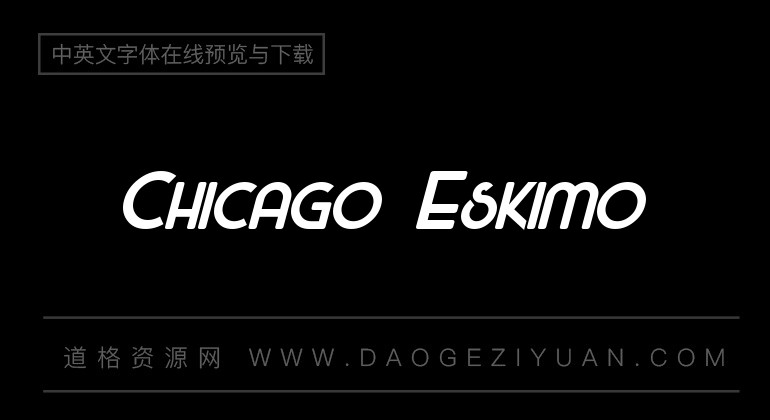
Chicago Eskimo
Chicago Eskimo 是一款美式经典报纸字体,由著名的美国字体设计师David Berlow于1991年创作。它是一种细腻、明快的黑体字体,具有精致的细节和优美的曲线,可以很好地展现出文字的细节和结构。它的字形简洁而不失精致,适用于报纸、杂志、书籍等出版物的排版。
Chicago Eskimo是一款非常不错的手写艺术字体,具有很好的视觉感,适合于文化类的宣传设计、商业类品牌的广告和产品包装设计以及个性化文字排版等较多场景。